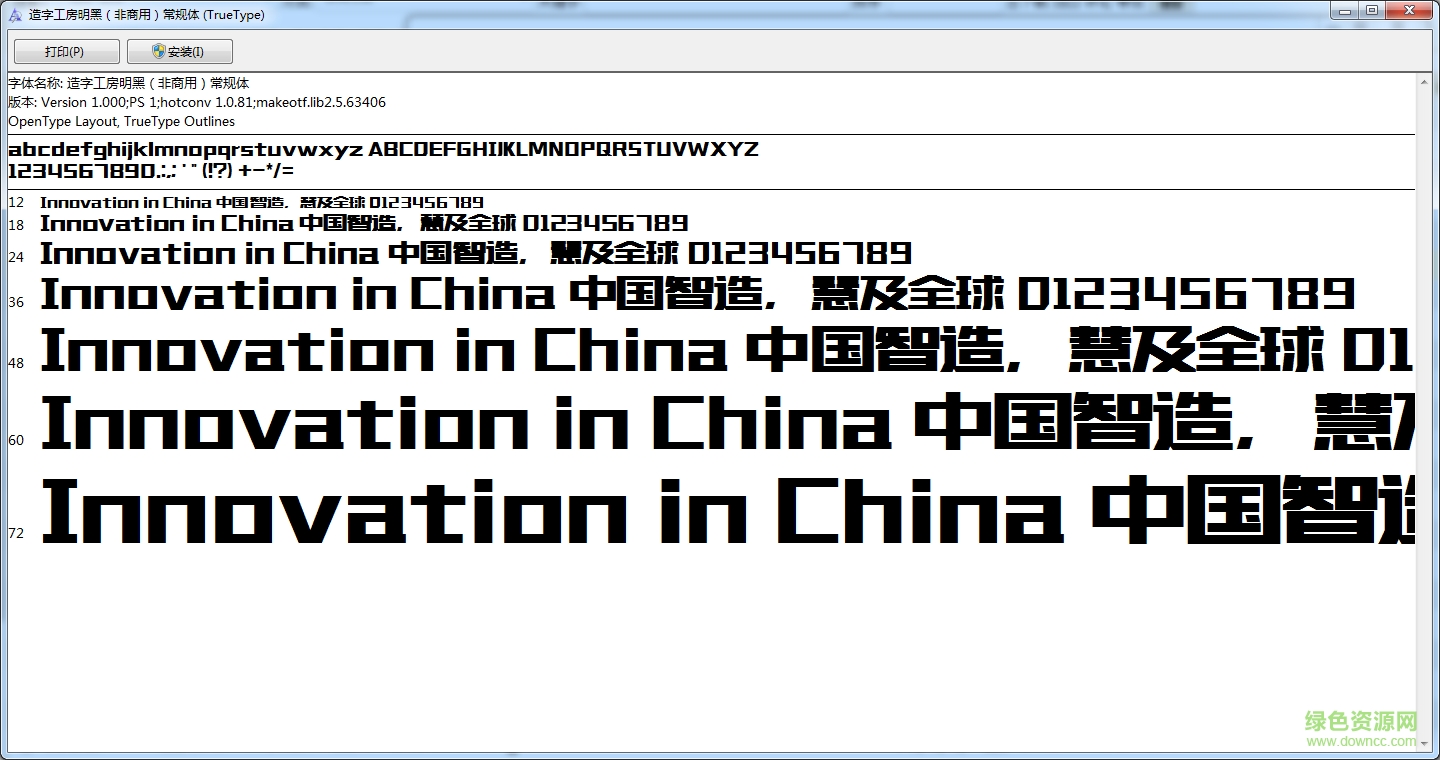
mfminghei_non是什么字體?mfminghei字體就是造字工房明黑(非商用)常規(guī)體,該字體結(jié)構(gòu)明朗,筆畫剛勁有力,透漏出一種沉穩(wěn)的氣質(zhì),可以用于品牌設(shè)計、平面設(shè)計、標(biāo)題排版等方面~!
1.字形扁平,筆畫清晰而飽滿,厚重工穩(wěn),遒勁有力,剛毅而不失俊朗,且直角的處理更顯剛毅,有極強(qiáng)的視覺表現(xiàn)力。
2.此款字體適用于主副標(biāo)題,有著較大范圍的應(yīng)用空間。